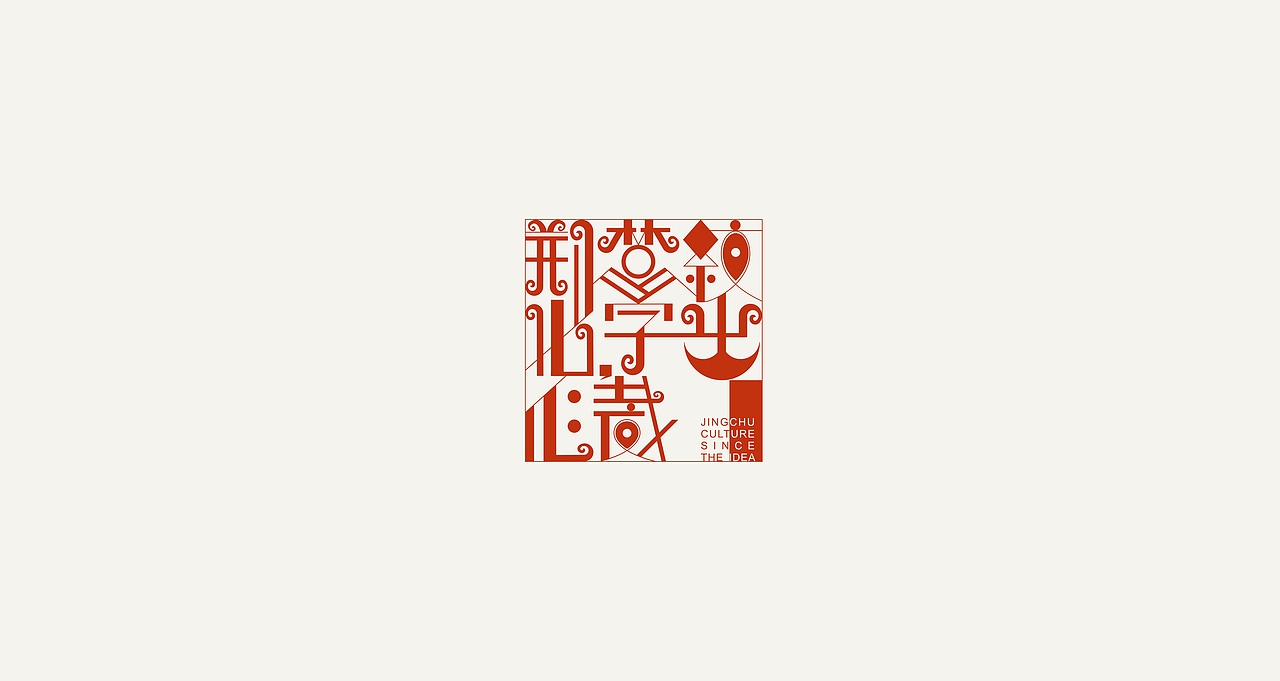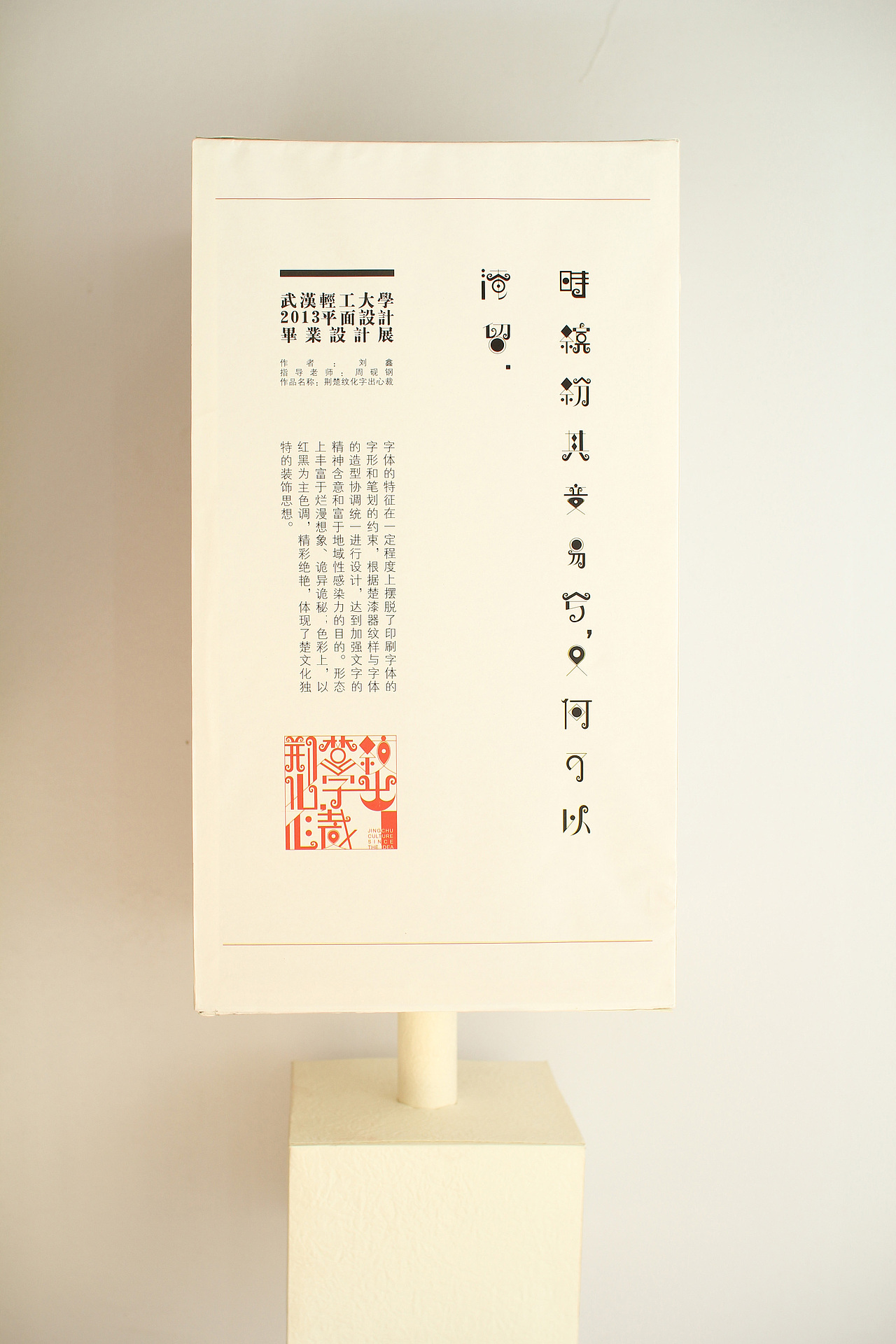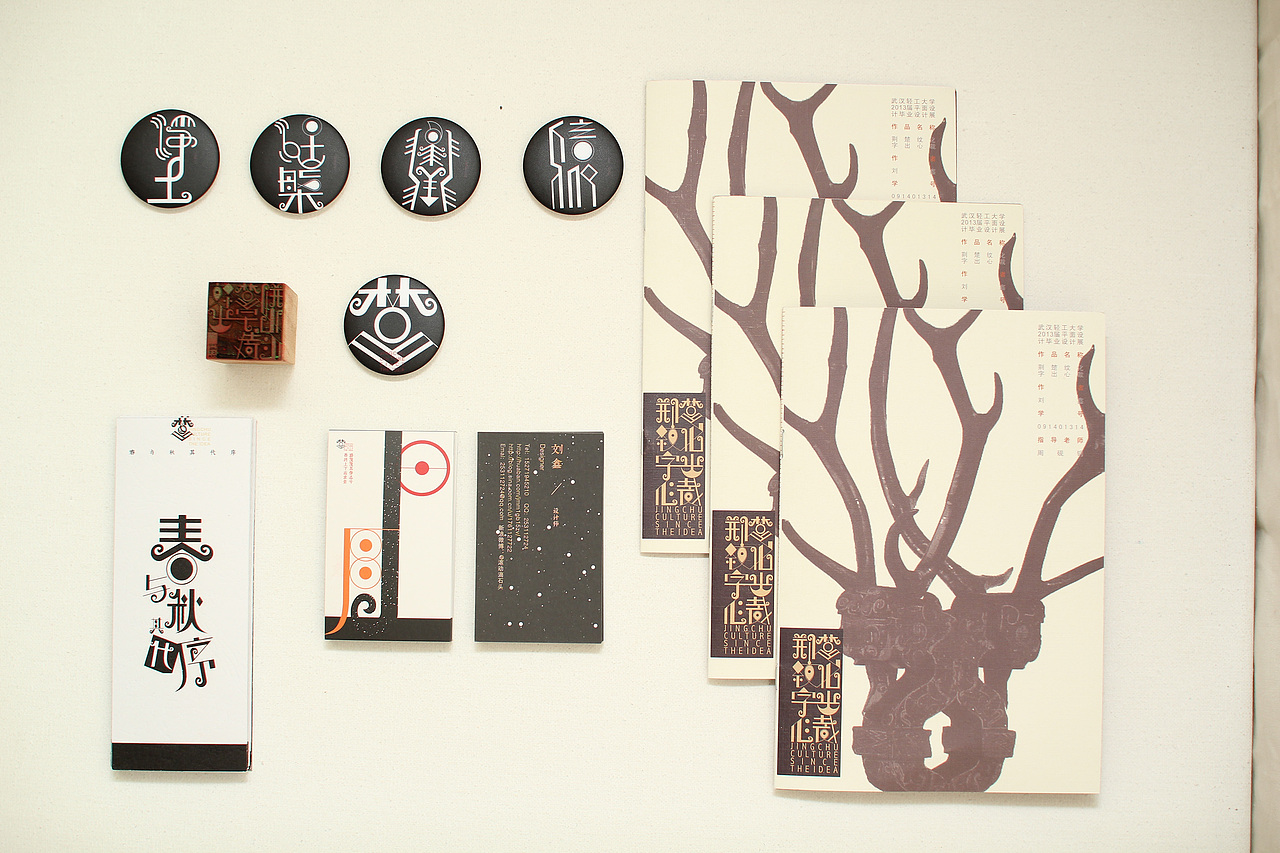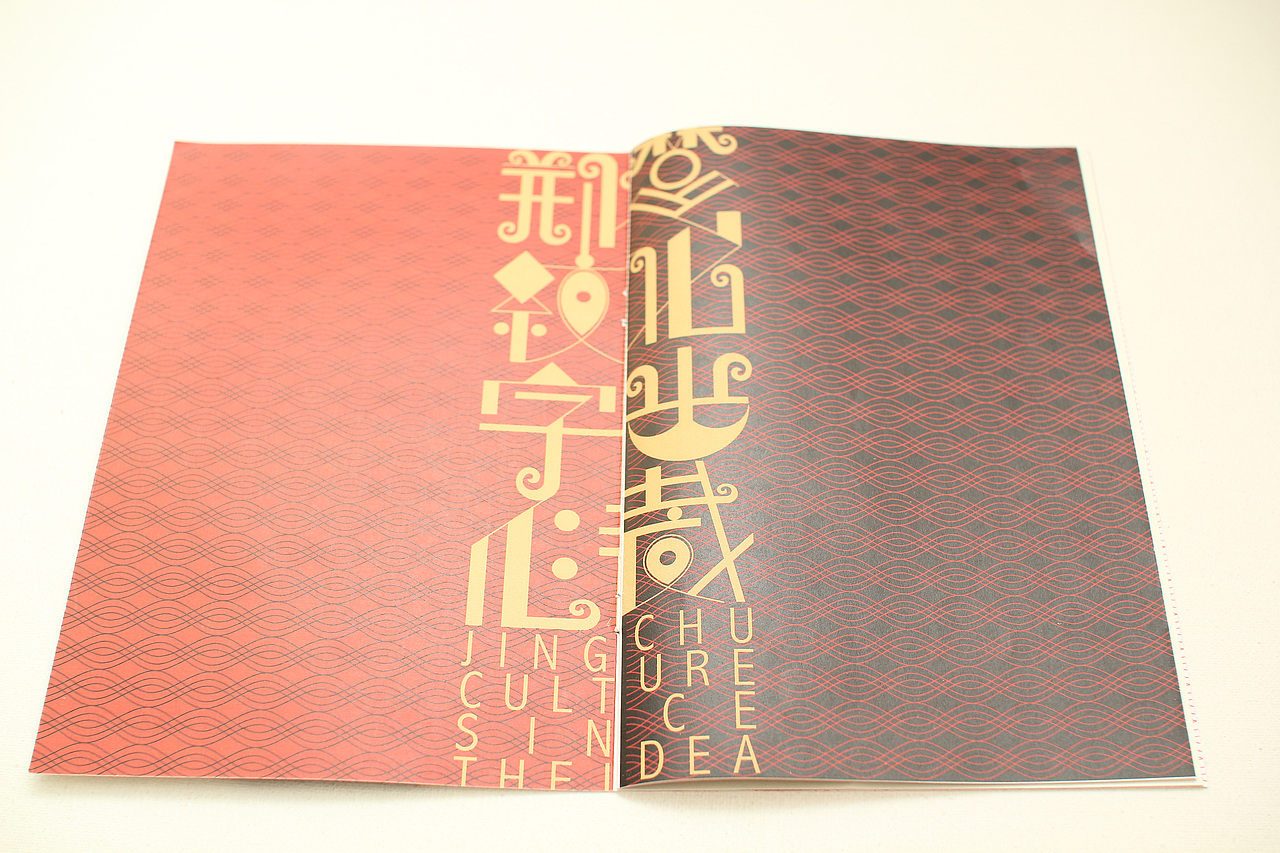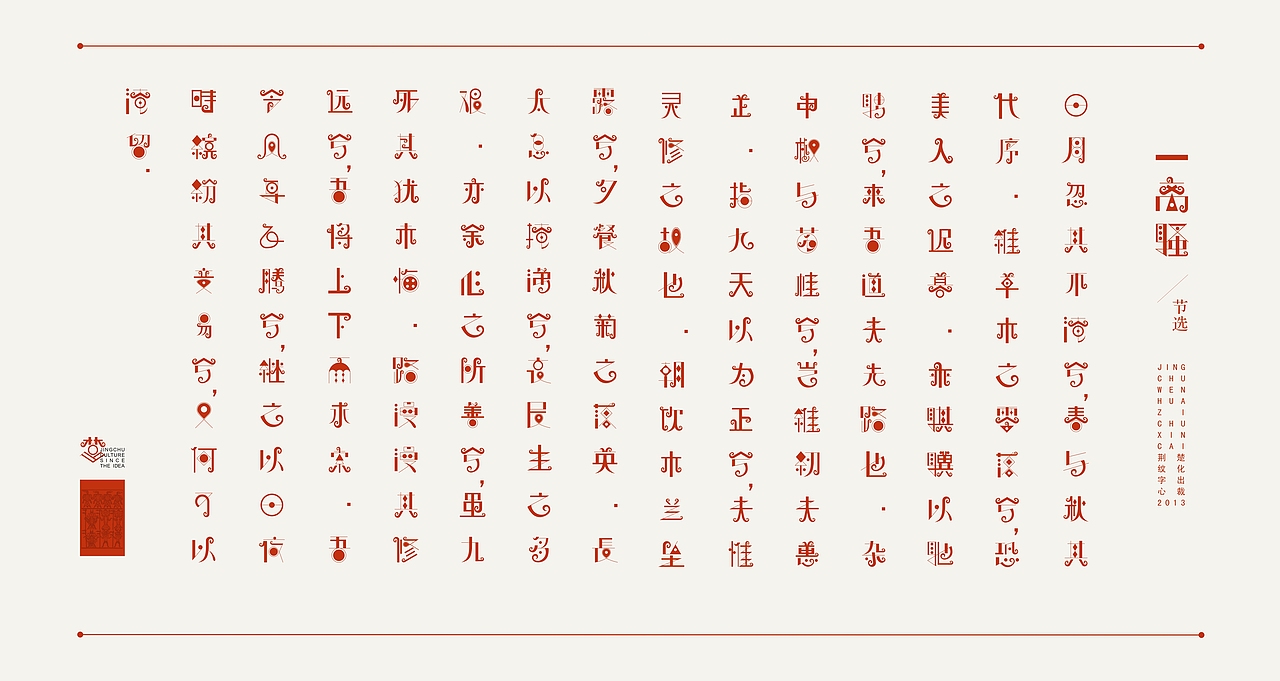
毕业设计#楚纹样字体设计
通过对楚纹样的概括、类型分析与自己对汉字字体造型笔画、结构等造型理解,提取纹样中基本元素的情感表达,去探索字体与纹样之间的关系。在把握现代汉字设计作品的“民族意味”和“时代特征”,研究中国传统纹样如何在现代汉字设计中的传承与再现。
荆楚纹化 字出心裁设计的灵感主要来自楚国漆器纹样,需要做的是提取纹样特殊符号与字体的造型协调统一进行设计,在了解纹样相关文化之后,开始策划心中的想法。
正因为创意字体的变化比较自由,强调字与字之间的统一与完整就显得特别重要。在一幅字中把每个字都装饰耐看些,注意它们之间的相互联系,寻找“共相”,在纷乱芜杂,变得和谐。 字体的特征在一定程度上摆脱了印刷字体的字形和笔划的约束,根据楚漆器纹样与字体的造型协调统一进行设计,达到加强文字的精神含意和富于地域性感染力的目的。
在完成离骚片段字体设计后,对掌握好的基本技巧,运用的字体海报设计 中,如果直搬放上去,未免有点呆板,在内容里,文字天生有着组合的特性,分析四个词组并结合篆书,宋体的结构来寻找切入点,净土中净字的末笔与净土中土字的起笔发生联系;涅槃中涅字的水旁与土旁为创意点;
翱翔给人的第一感受是飞鸟在天空翱翔的感觉,两个字同样有个羽旁,做出那种鸟向上冲的感觉,把日旁变成鸟的眼睛和嘴,羽旁左右平分,像鸟展开的一对翅膀;信仰两字左边都有个人旁,在设计中放在一起又是同一边会显得左边是一个整体,与右边没有联系,为避免,我把信字的人旁镜像翻转,刚好与仰字巧妙联系,整个设计就成一体了。
我想一件好的视觉创达作品不因限制于我们所看到的,在这件作品中,一定程度的让公众参与其中,一定程度的与公众产生身体与精神上的交流,从而能给与人们最全方位的感受。
是一个互动式灯光装置作品,作品结合了 LED 与 木质框架纸质包裹的组合,装置在灯亮前与灯亮后变化出各种不同色彩的字形, 这个装置旨在与参观者之间创造一个视觉对话平台,观众通过拍掌或脚步声控制作品,通过观众的变化,作品给与“互动回应”,视觉与音效上产生相应的变化。这个装置通过将视觉感知思想并置,把所设计好的纹字与现代的元素相结合,把作品,公众,空间三者结合起来。